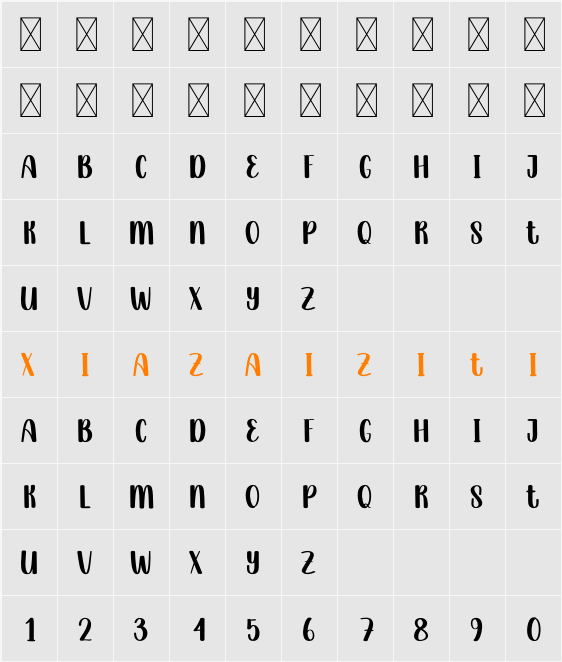
Youthful
Youthful,这款字体结构工整、笔画清晰,兼顾美观与易读性,适用于标题、正文、海报、包装、LOGO 等多种场景。字形优雅稳定,风格百搭耐看,适配日常排版与创意设计,让文字呈现更舒适、更具质感。Youthful一笔一画,皆是细节,以均衡的比例、流畅的线条打造舒适视觉体验,字形端正大气,风格简约现代。无论是商业设计、品牌宣传还是日常排版,都能轻松驾驭,让文字更有格调与力量。Youthful字体下载。